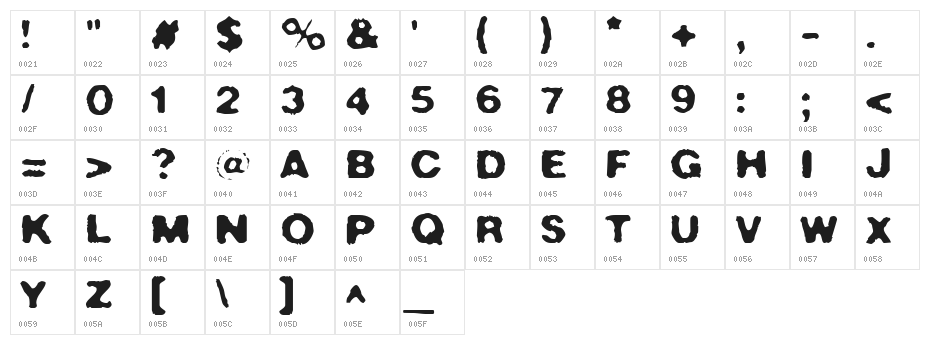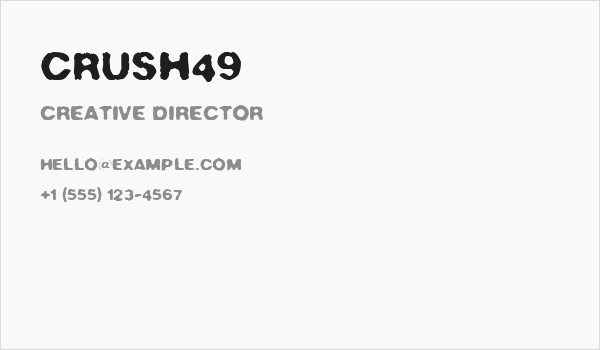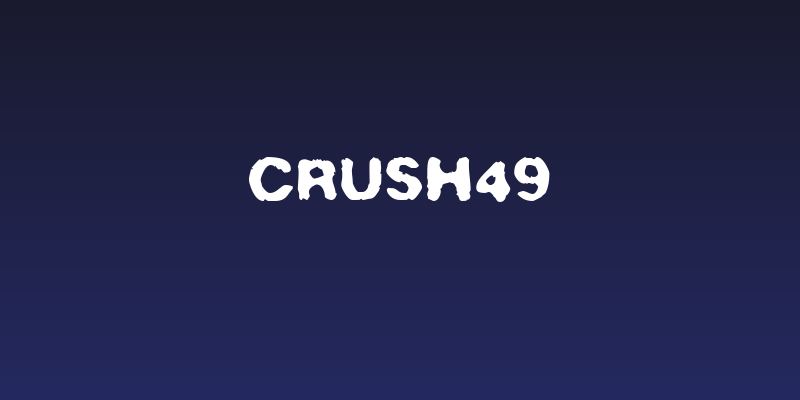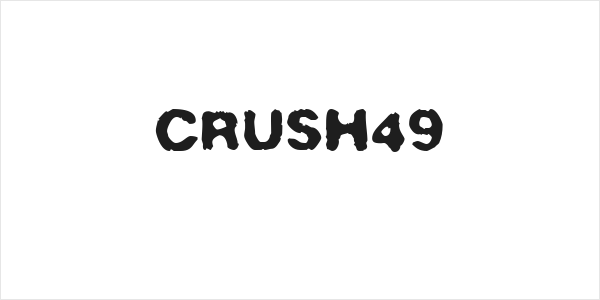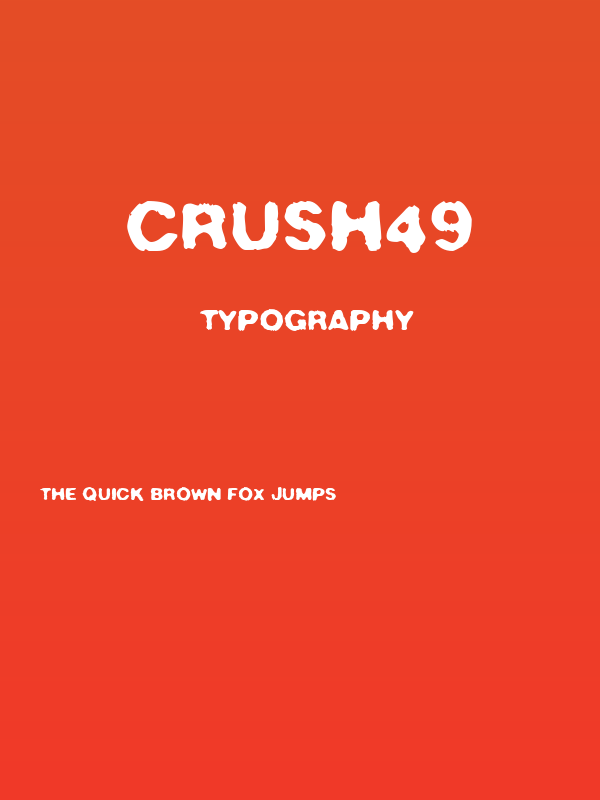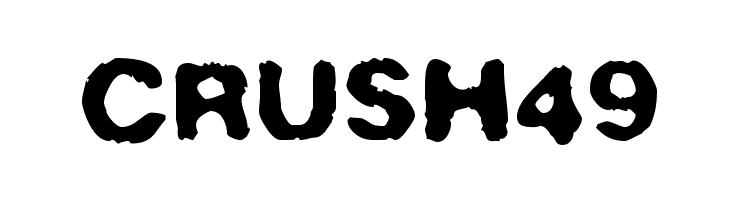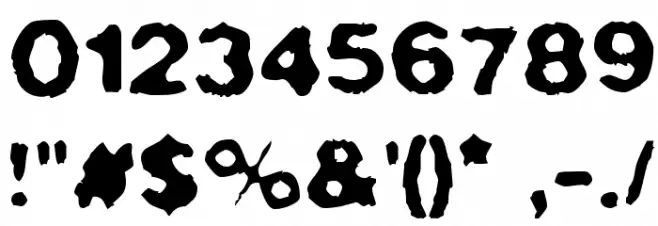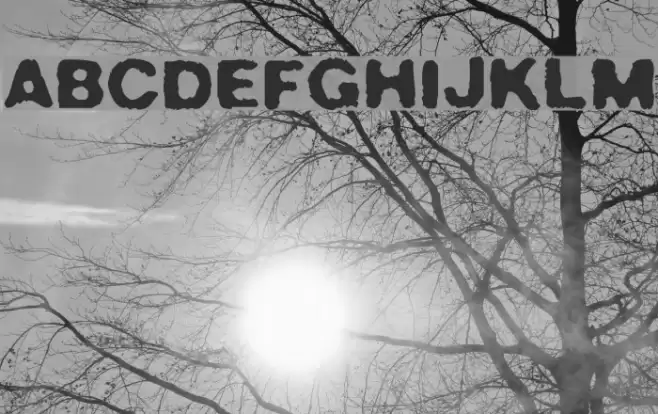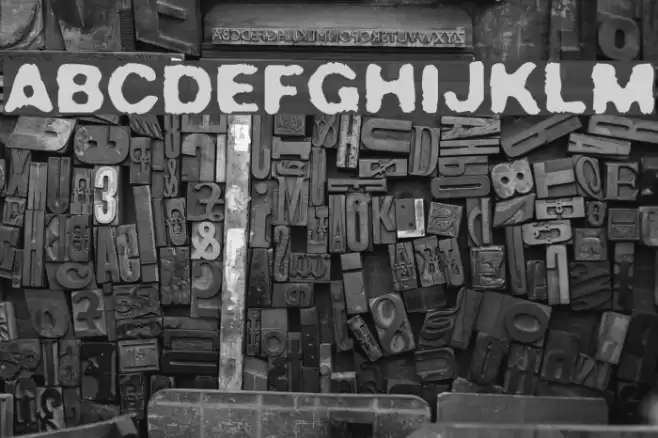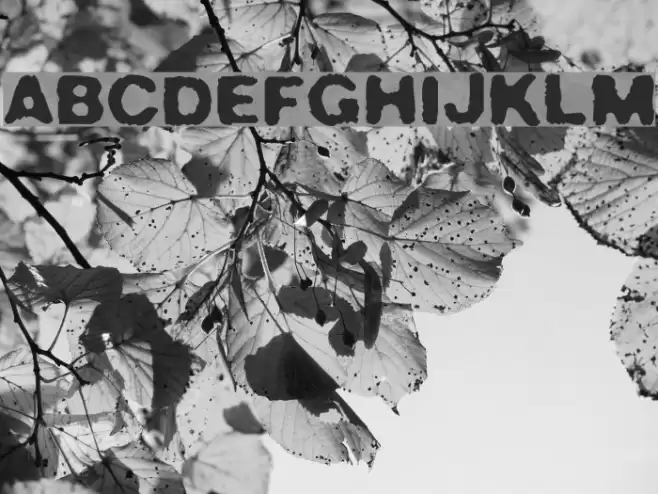
Crush49 Font
✎ Messy
| Projets proposés | Ideal for posters, album covers, branding for edgy products, or any design needing a bold, impactful statement. |